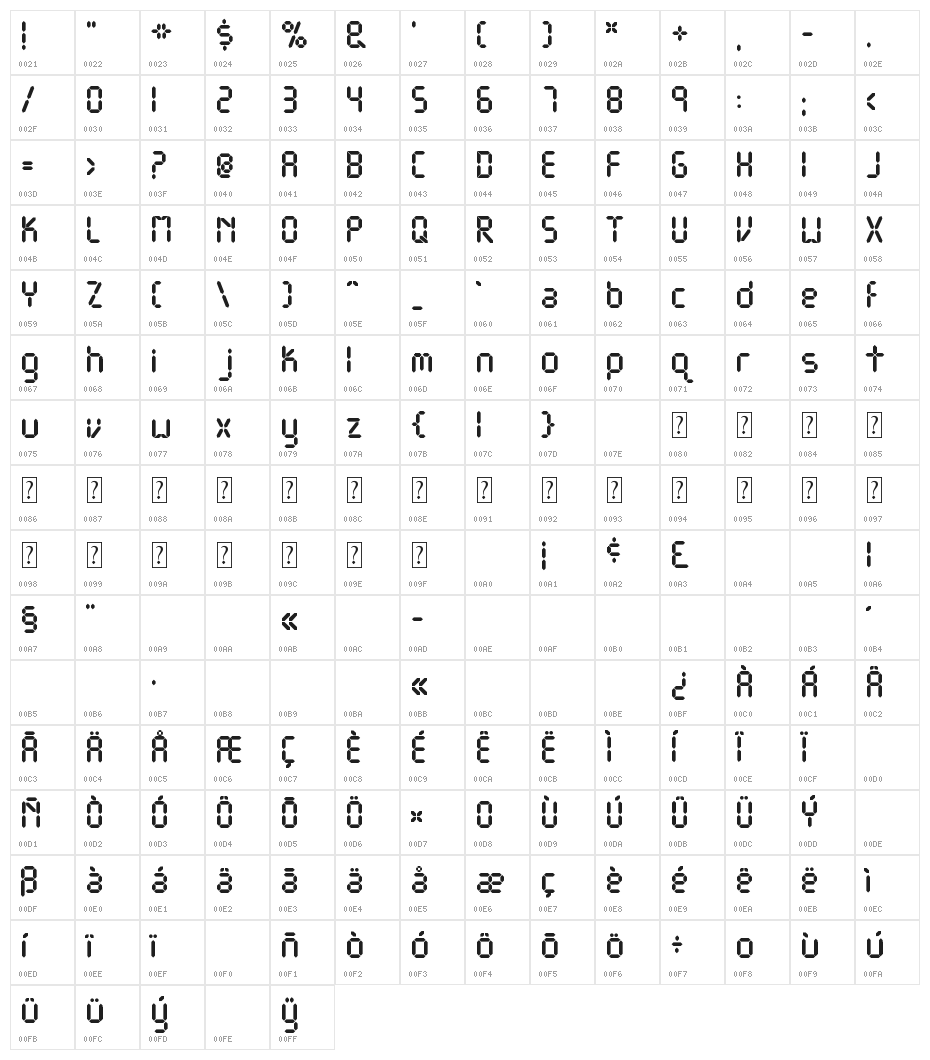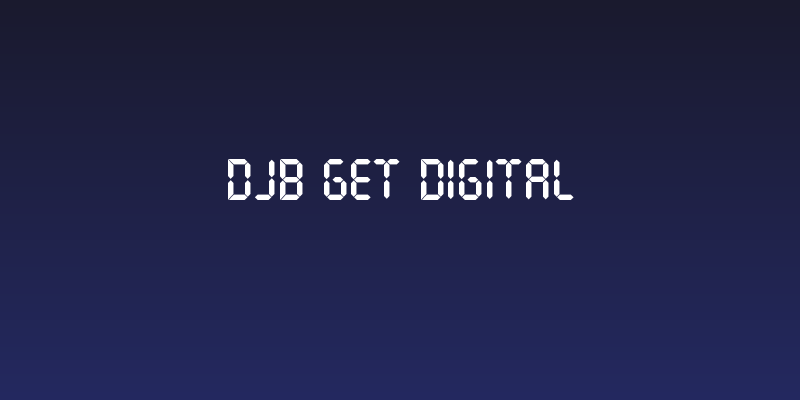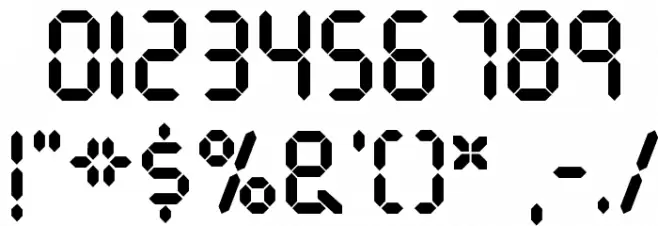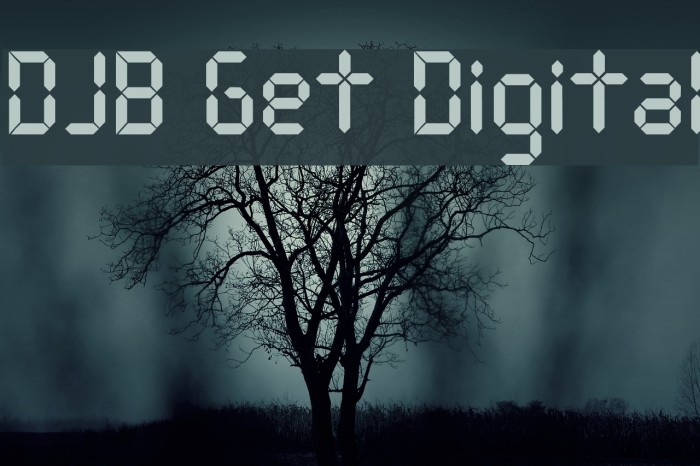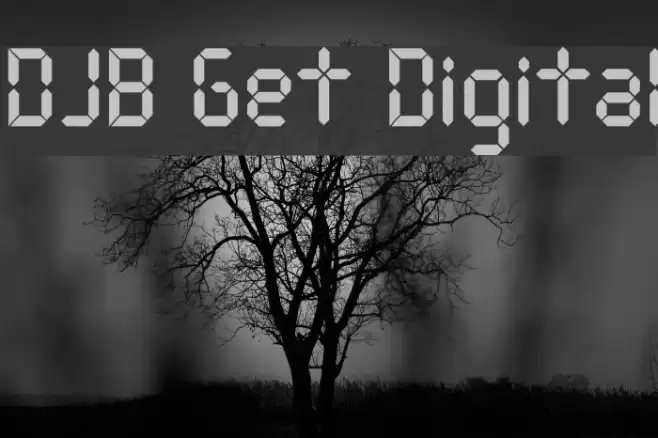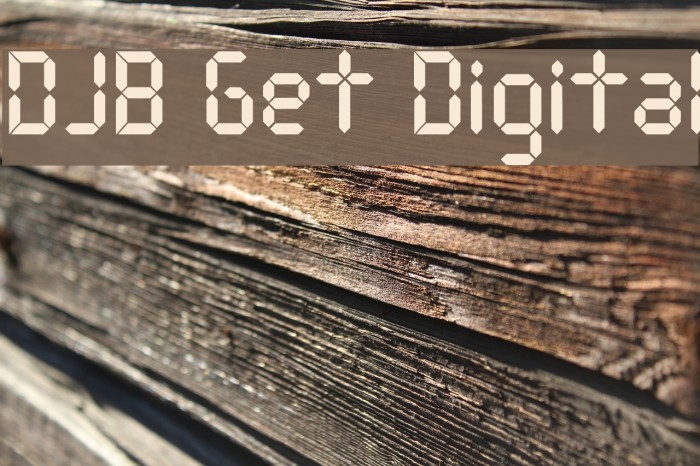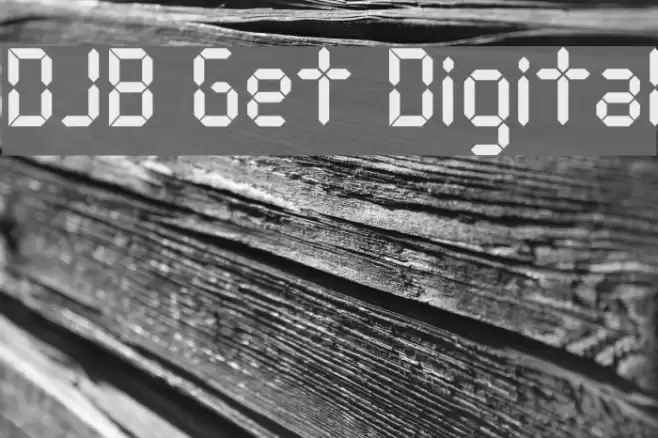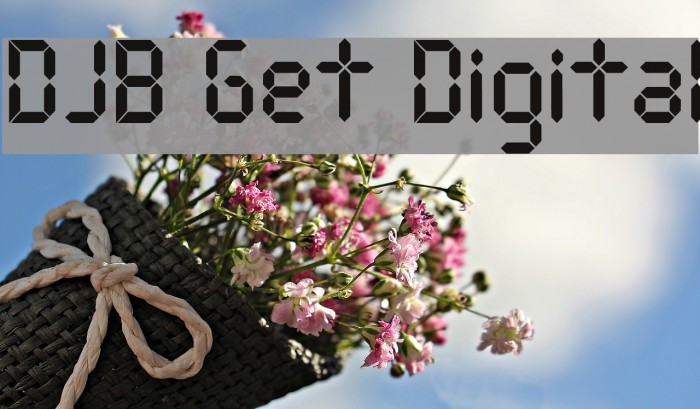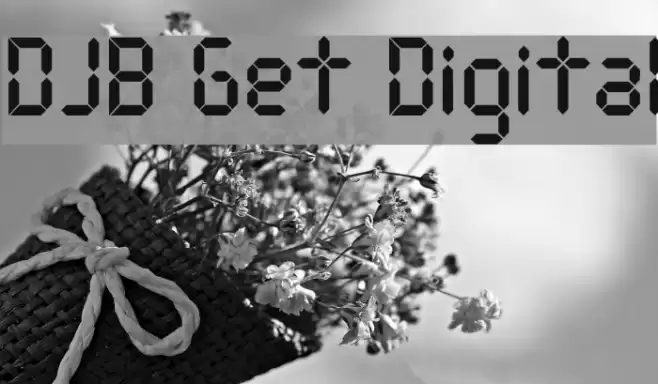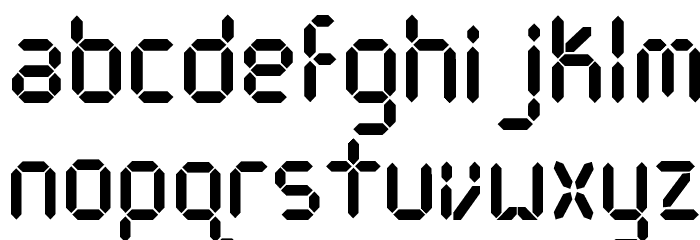
DJB Get Digital Font
Fonts by Darcy Baldwin {fontography}
DJB-GET-DIGITAL 大文字
DJB-GET-DIGITAL 小文字
DJB-GET-DIGITAL その他の文字
| 用途 | Headlines, Logos, Digital displays |
| おすすめプロジェクト | Ideal for digital interfaces, tech-themed posters, video game graphics, and futuristic branding. |